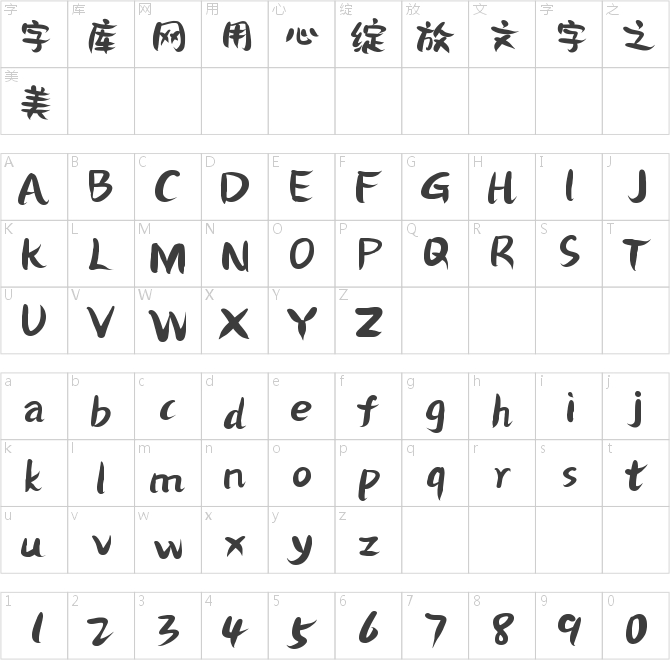
字魂258号-儿歌体
• 字魂258号-儿歌体是一款可爱的创意字,该字体笔画呆萌随意,非常的养眼,创意十足,可以广泛应用于名片设计、包装设计、网页设计、新闻媒体、宣传海报、ppt、影视制作以及内容用字等领域。
字魂258号-儿歌体字体ZiHun258Hao-ErGeTi字库是一款让人赏心悦目、百看不厌的中文字体,适合各类广告和产品包装设计应用,字体大小12.63MB,格式为ttf字体,上传用户是张海燕呐,作者/版权方为字魂